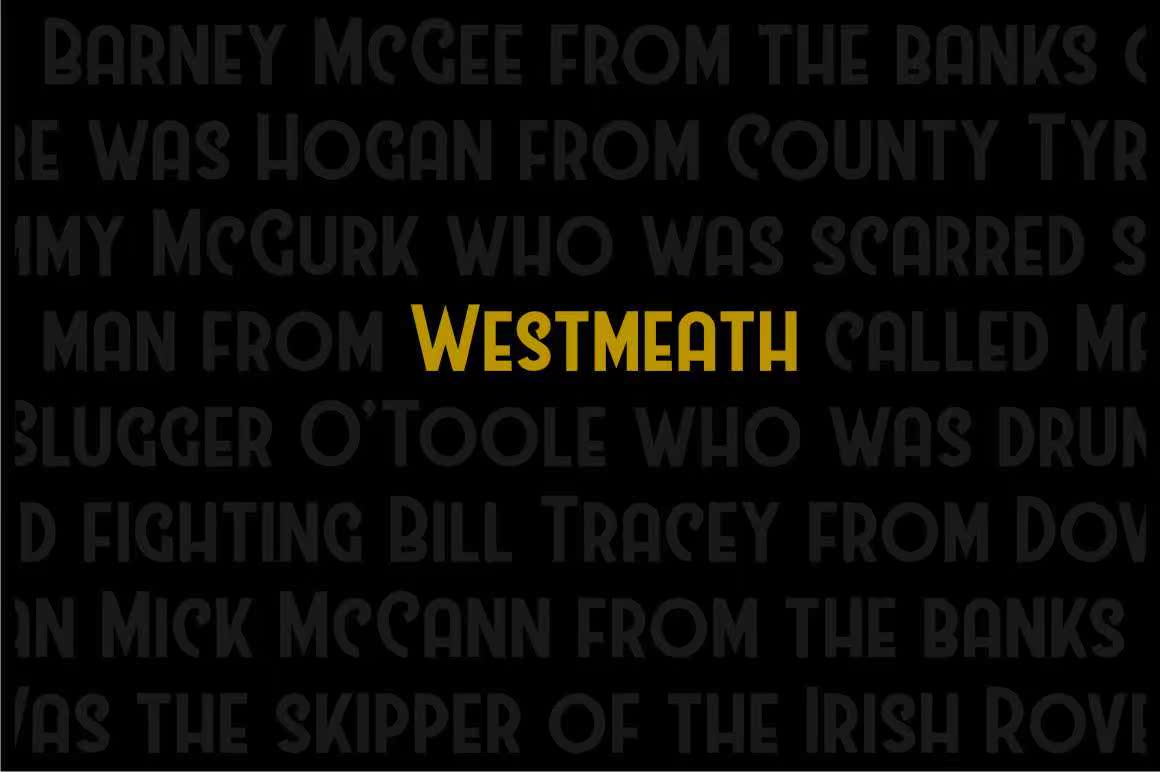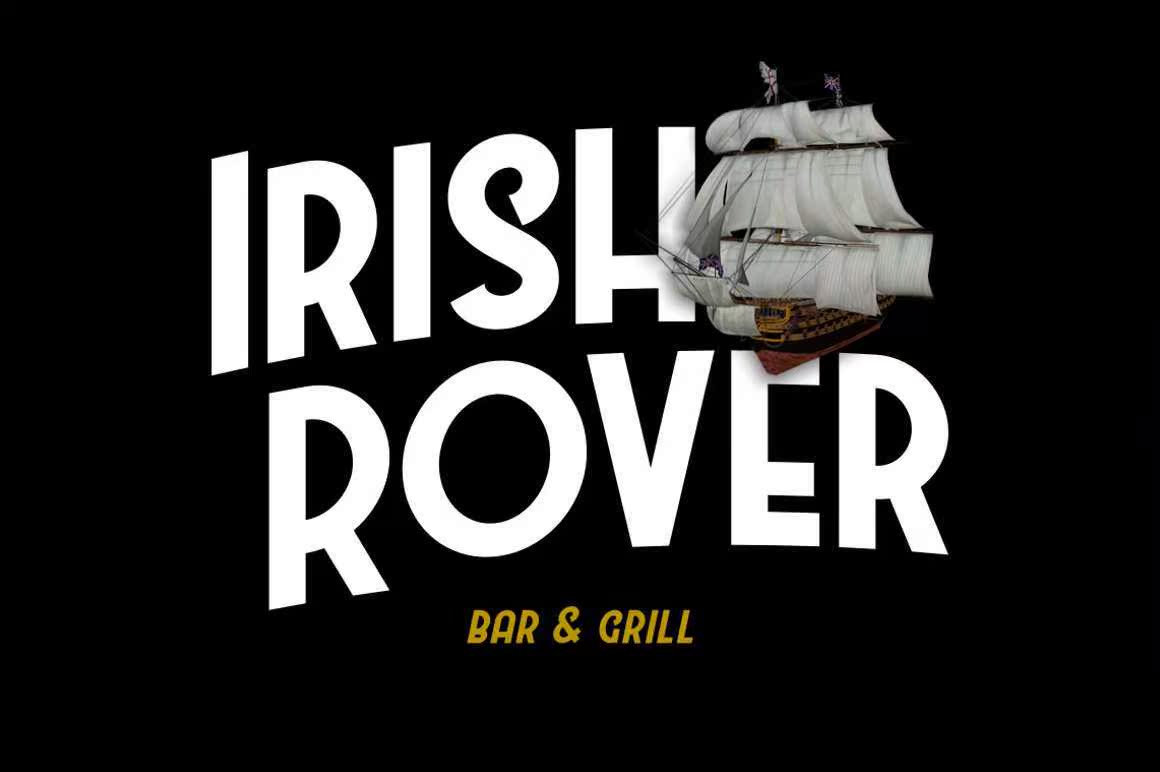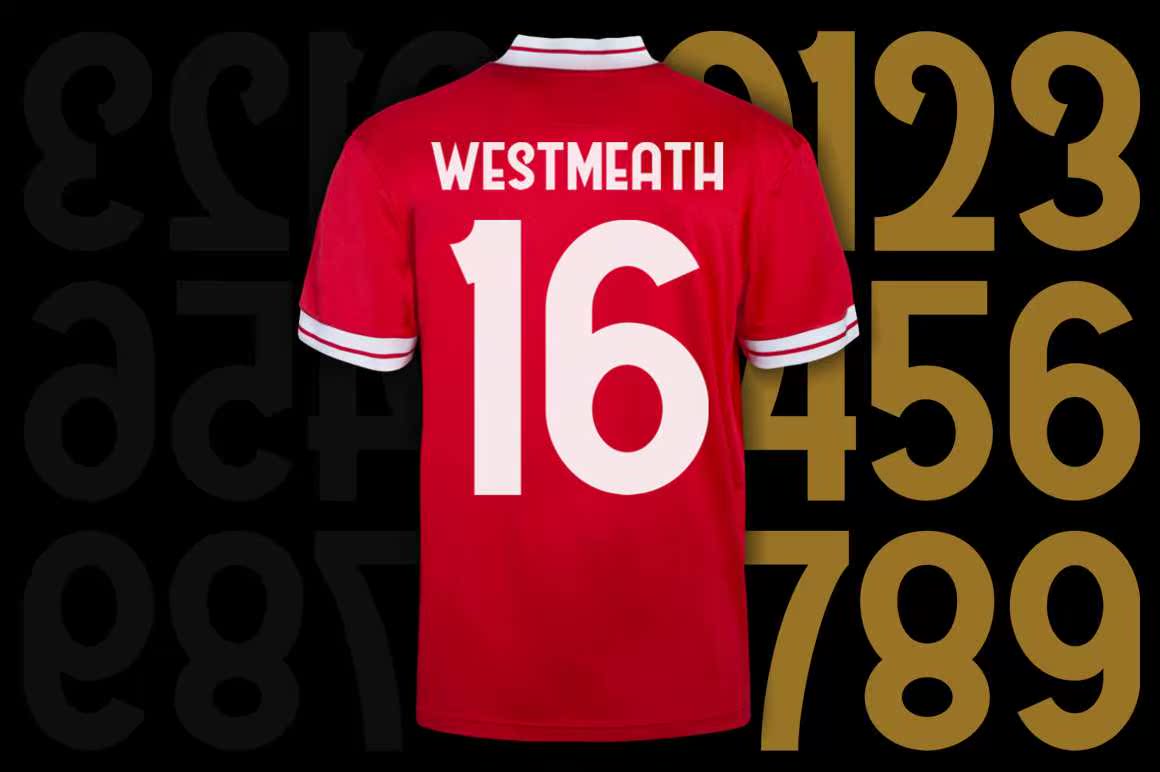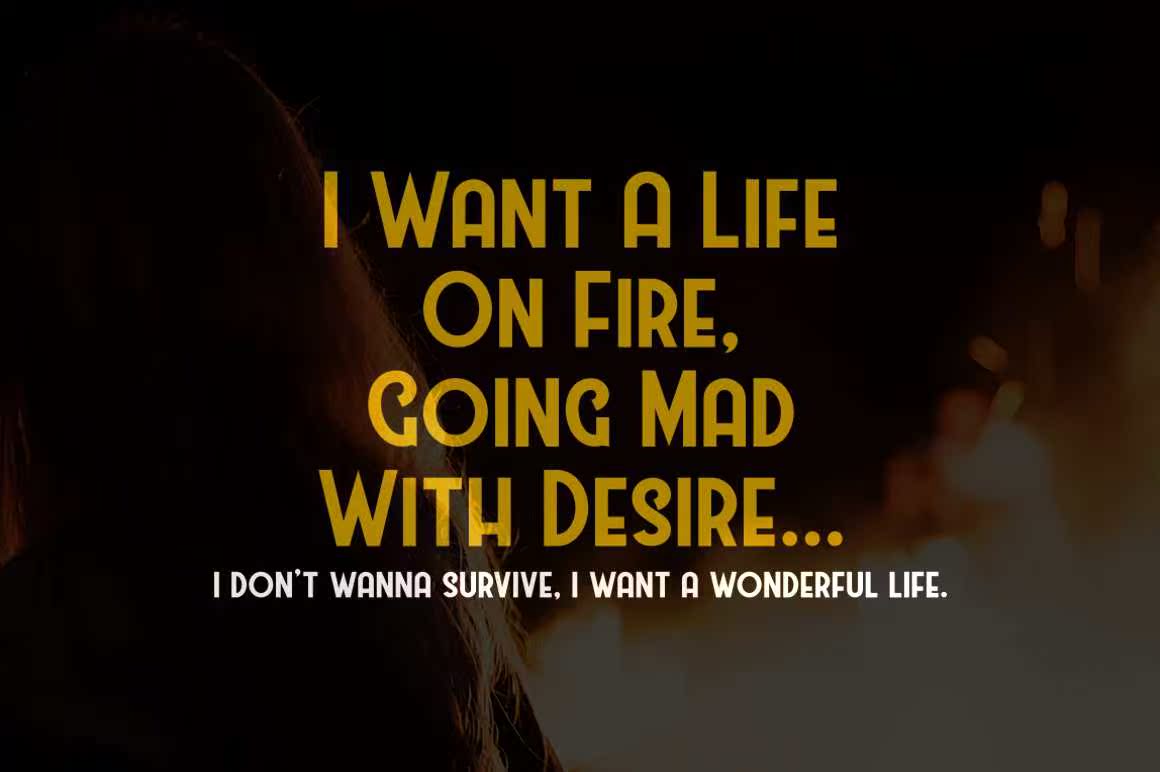
引种新蕨类植物;Westmeath.Aclensansserif,bitfat(但我们相信这一款看起来仍然很性感),还有Art deco ish,等等,当然还有“经典/葡萄酒风格”。有两种款式可供选择:常规的和意大利的。Justincase You Guy Undering,是的,这款香水对个人和商业用途都是免费的;Westmeath.Aclensansserif,bitfat(但我们相信这一款看起来仍然很性感),还有Art deco-ish,等等,当然还有“经典/葡萄酒风格”。有两种款式可供选择:常规和传统。Justincase You Guy Swendering,是的,这款香水是免费供个人和商业使用的。